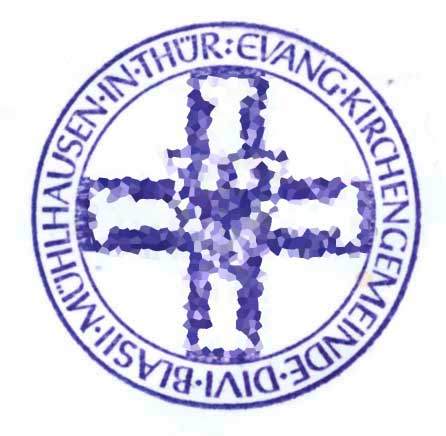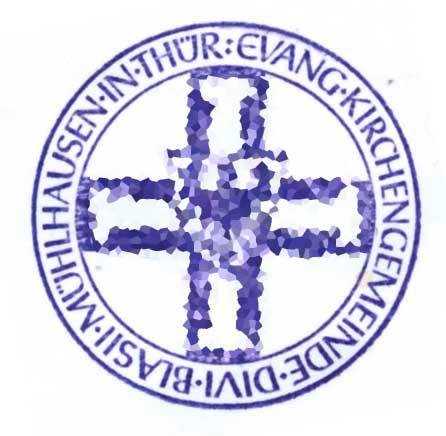
Suche "evangelische Schriftart"
Ich lese schon länger immer mal wieder interessiert in diesem Forum und muss nun doch einmal eine Frage loswerden. Es geht um die Schrift, die in einem Kirchensiegel verwendet wurde (siehe Dateianhang; leider habe ich keine bessere Vorlage). Ohne es konkret festmachen zu können, meine ich doch, im kirchlichen Kontext schon häufig dieser Schrift begegnet zu sein, was mich hoffen lässt, dass es sich um eine Satzschrift handelt.
Ich würde gern wissen, ob diese oder eine Schrift mit ähnlichem Duktus den Übergang ins Digitalzeitalter überstanden hat – und wenn ja, unter welchem Namen :-).
Ah, ganz herzlichen Dank :bow:! Die Post-Antiqua kannte ich sogar; manchmal sieht man den Wald vor lauter Bäumen nicht ...
Bei der Schrift im Siegel kam mir auch ganz schnell Rudolf Koch in den Sinn. Interessant, dass tatsächlich sein Filius bei der Post-Antiqua die Finger im Spiel hatte.
Zumindest der Duktus ist ja in der Tat bei "der Post" und der Scriptuale sehr ähnlich. Verzichten müsste ich da auf das "runde" E. Der Gestalter der Ausgangsschrift scheint sich – bei grundsätzlich ähnlicher Absicht – noch etwas mehr an der Unziale orientiert zu haben? Mit der Abweichung kann ich leben. Schwieriger sind wohl die Umlaut-Pünktchen. Ich soll/darf/muss/kann das oben angehängte Siegel nämlich nachbauen und mit geänderter Beschriftung neu setzen.D.h.: weiterhin kein Platz für "herausragende Tüddelchen". Ich meine mich zu erinnern, dass das erst kürzlich hier Thema war :-D
Verzichten müsste ich da auf das "runde" E.
Interessant ist, dass diese nur einmal am Wortanfang zum Einsatz kam. Selbst dieses könnte man beispielsweise aus dem C und E nachempfinden, wenn man das wöllte.
Ja, genauso werde ich das machen – also von Hand ein wenig nachhelfen :hammer: